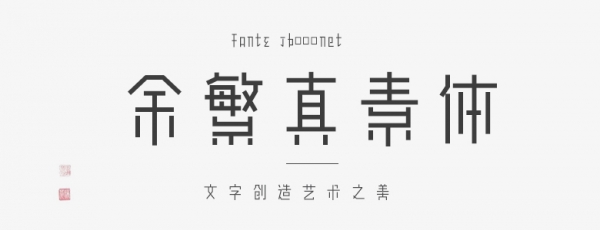
上次說到要體系化字體的視覺平衡,花了將近四個(gè)月的時(shí)間才搞定。
現(xiàn)理論對(duì)于正字類字體還稍顯不足,但對(duì)簡(jiǎn)單創(chuàng)意類字體是手拿把掐。
這個(gè)版本的真素體完全重制花了兩星期,對(duì)于把一個(gè)點(diǎn)子拓展成一個(gè)中文字體而言,這樣的時(shí)間開銷勉強(qiáng)算是可以接受了。
寫得跟數(shù)學(xué)書一樣的字形平衡理論估計(jì)在站酷沒幾人想看,單貼點(diǎn)圖看看具體效果哈。